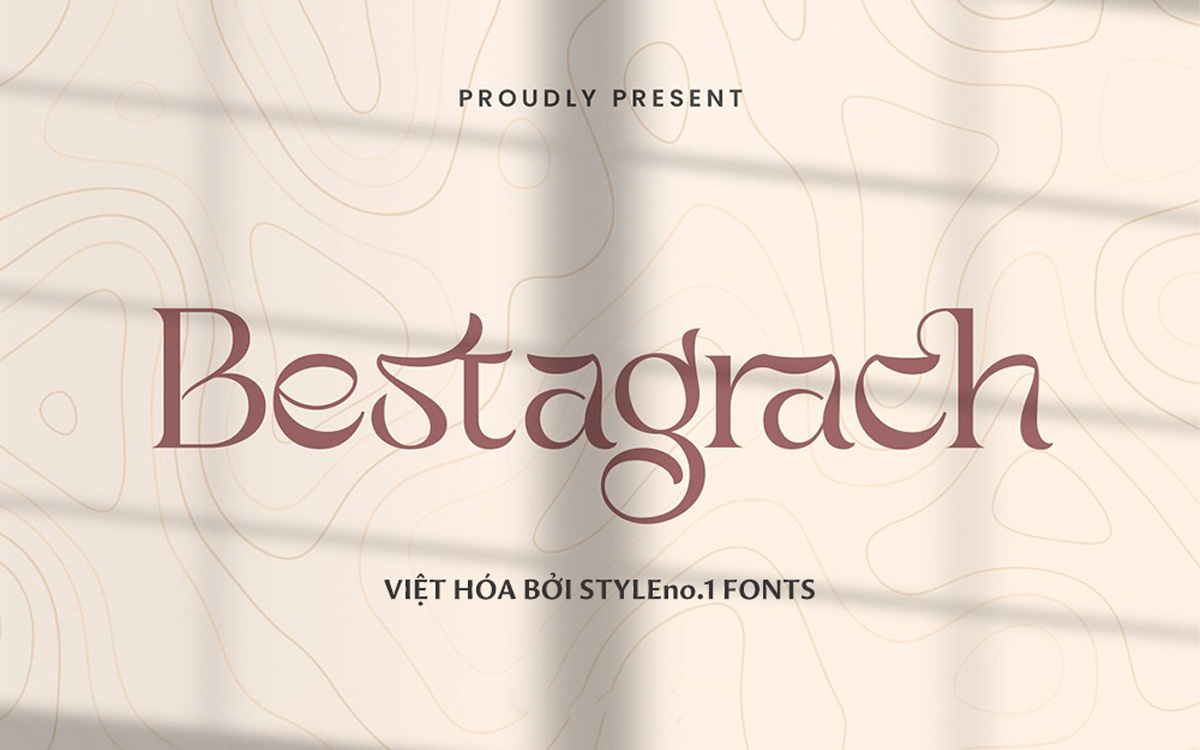
Trong thế giới thiết kế đồ họa hiện đại, việc lựa chọn một phông chữ phù hợp không chỉ dừng lại ở khả năng truyền tải thông điệp mà còn thể hiện thần thái và cá tính riêng của thương hiệu. Font chữ thanh lịch SVN Bestagrach Việt Hoá chính là sự kết hợp hoàn hảo giữa nét đẹp quyến rũ cổ điển và tinh thần hiện đại đầy tinh tế. Được tối ưu hóa hoàn toàn cho chuẩn tiếng Việt, đây chắc chắn là công cụ đắc lực dành cho các nhà thiết kế đang tìm kiếm sự đột phá trong các dự án cao cấp.</p>
Khám Phá Font Chữ Thanh Lịch SVN Bestagrach Việt Hoá – Đỉnh Cao Của Nghệ Thuật Typography Sang Trọng
Một bộ font chữ đẹp không đơn thuần là những ký tự nối tiếp nhau, mà nó là linh hồn của tác phẩm nghệ thuật đồ họa. SVN Bestagrach Việt Hoá ra đời nhằm đáp ứng nhu cầu khắt khe của các designer chuyên nghiệp trong việc kiến tạo những sản phẩm truyền thông mang tính thẩm mỹ cao. Với cấu trúc nét chữ được gọt giũa tỉ mỉ, độ tương phản nét thanh nét đậm chuẩn xác, phông chữ này tự tin làm nổi bật mọi tiêu đề, logo hay ấn phẩm cao cấp.
Việc chuyển ngữ và Việt hóa trọn bộ giúp SVN Bestagrach loại bỏ hoàn toàn rào cản về mặt ngôn ngữ. Các dấu thanh tiếng Việt được tạo hình chỉn chu, giữ nguyên tỉ lệ vàng của bộ phông gốc, giúp văn bản hiển thị tự nhiên, không bị xô lệch hay mất cân đối. Hãy cùng đi sâu vào những tính năng đặc sắc giúp font chữ thanh lịch SVN Bestagrach Việt Hoá trở thành lựa chọn ưu tiên hàng đầu hiện nay.
1. Đường Nét Thiết Kế Uốn Lượn Tinh Tế Và Mang Đậm Tính Nghệ Thuật
Điểm ấn tượng đầu tiên của SVN Bestagrach nằm ở đường nét uốn lượn mềm mại nhưng vẫn giữ được sự vững chãi cần thiết. Mỗi ký tự đều được chăm chút kỹ lưỡng, tạo nên nhịp điệu thị giác êm ái khi đọc. Sự đan xen giữa các đường cong uyển chuyển và nét thẳng dứt khoát giúp bộ font này mang lại cảm giác vô cùng sang trọng, quý phái.
Phong cách này cực kỳ thích hợp cho các thương hiệu thuộc lĩnh vực thời trang cao cấp, mỹ phẩm, trang sức hay các không gian kiến trúc xa xỉ. Sử dụng SVN Bestagrach trên các ấn phẩm quảng cáo sẽ ngay lập tức nâng tầm giá trị sản phẩm, thu hút ánh nhìn của khách hàng thượng lưu ngay từ cái nhìn đầu tiên.
2. Tối Ưu Hóa Tiếng Việt Trọn Bộ Với Chuẩn Ký Tự Việt Hoá Mượt Mà
Một trong những nỗi băn khoăn lớn nhất của các designer Việt Nam khi sử dụng các bộ font quốc tế là tình trạng lỗi font khi gõ dấu tiếng Việt (như các dấu hỏi, ngã, nặng, sắc, huyền hoặc các chữ có dấu mũ như ê, ô, ơ, ư). Với SVN Bestagrach Việt Hoá, vấn đề này đã được giải quyết một cách triệt để.
Tác giả bản Việt hóa đã nghiên cứu kỹ lưỡng vị trí và kích thước của các dấu thanh sao cho hài hòa tuyệt đối với hình dáng ký tự gốc. Kết quả là chúng ta có một bộ font tiếng Việt chuẩn chỉnh, các ký tự có dấu không bị đè lên nhau, khoảng cách dòng (leading) và khoảng cách chữ (kerning) được tối ưu hóa tối đa, mang lại trải nghiệm thị giác mượt mà và chuyên nghiệp.
3. Bộ Ký Tự Thay Thế (Alternates) Và Ligatures Phong Phú
SVN Bestagrach không chỉ cung cấp các ký tự căn bản mà còn đi kèm với hệ thống tính năng OpenType vô cùng phong phú. Bộ font bao gồm hàng loạt ký tự thay thế (Stylistic Alternates) và các nét nối đặc biệt (Ligatures), cho phép bạn thỏa sức sáng tạo và biến hóa văn bản theo phong cách riêng.
Nhờ tính năng này, người thiết kế có thể dễ dàng tạo ra những cụm chữ (logotype) độc nhất vô nhị mà không cần tốn nhiều công sức chỉnh sửa thủ công từng đường vector. Bạn chỉ cần bật các tính năng OpenType trong các phần mềm như Adobe Photoshop, Illustrator hay InDesign để khám phá hàng trăm biến thể nét chữ độc đáo.
4. Khả Năng Ứng Dụng Đa Dạng Trong Nhiều Lĩnh Vực Thiết Kế
Mặc dù mang phong cách thanh lịch và sang trọng, SVN Bestagrach Việt Hoá lại có khả năng ứng dụng vô cùng linh hoạt trên nhiều chất liệu và định dạng sản phẩm khác nhau. Dưới đây là một số ứng dụng tiêu biểu của bộ font này:
- Thiết kế nhận diện thương hiệu: Tạo dựng logo, khẩu hiệu (tagline), danh thiếp và bộ nhận diện văn phòng cho các thương hiệu cao cấp.
- Ấn phẩm sự kiện & Thiệp cưới: Hoàn hảo cho việc thiết kế thiệp mời cưới, thiệp dạ tiệc, menu nhà hàng sang trọng và thiệp mừng sự kiện.
- Thiết kế bao bì sản phẩm: Tăng giá trị cho bao bì nước hoa, hộp mỹ phẩm, nhãn chai rượu vang hay hộp quà tặng cao cấp.
- Bìa sách & Tạp chí: Phù hợp làm tiêu đề cho các tạp chí thời trang, đời sống, nghệ thuật hoặc bìa các cuốn tiểu thuyết lãng mạn.
- Truyền thông Kỹ thuật số: Tạo điểm nhấn cho hình ảnh banner quảng cáo trên Facebook, Instagram, giao diện website thời trang và các chiến dịch Marketing online.